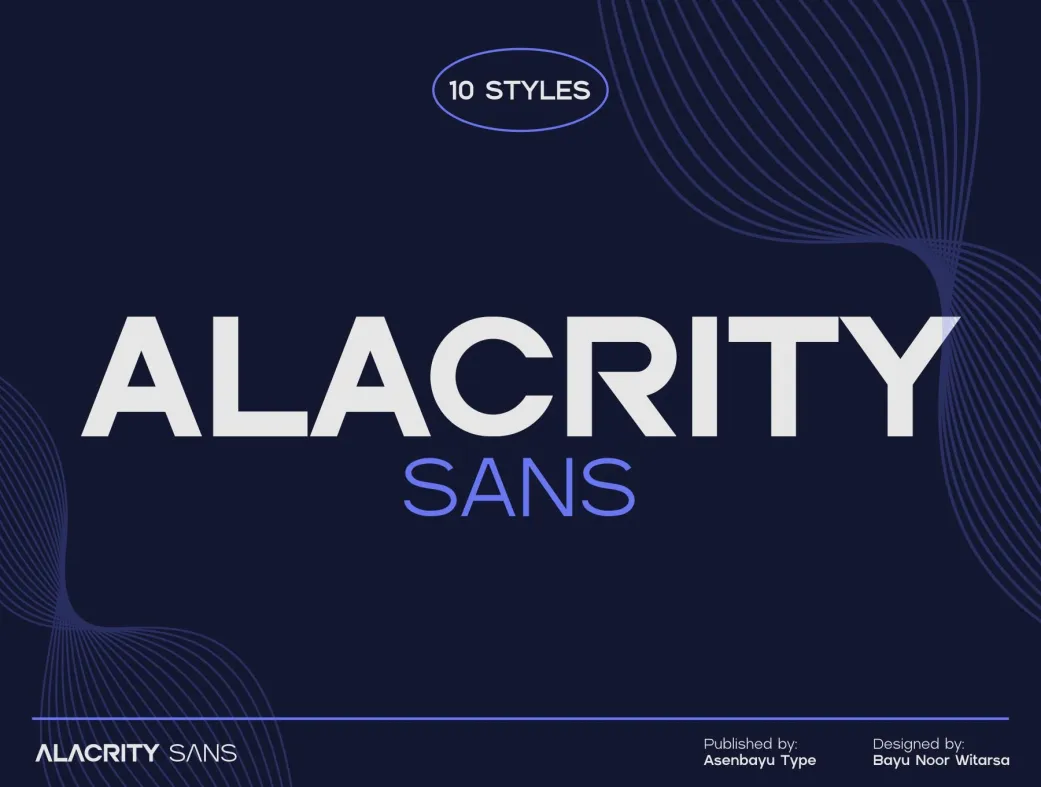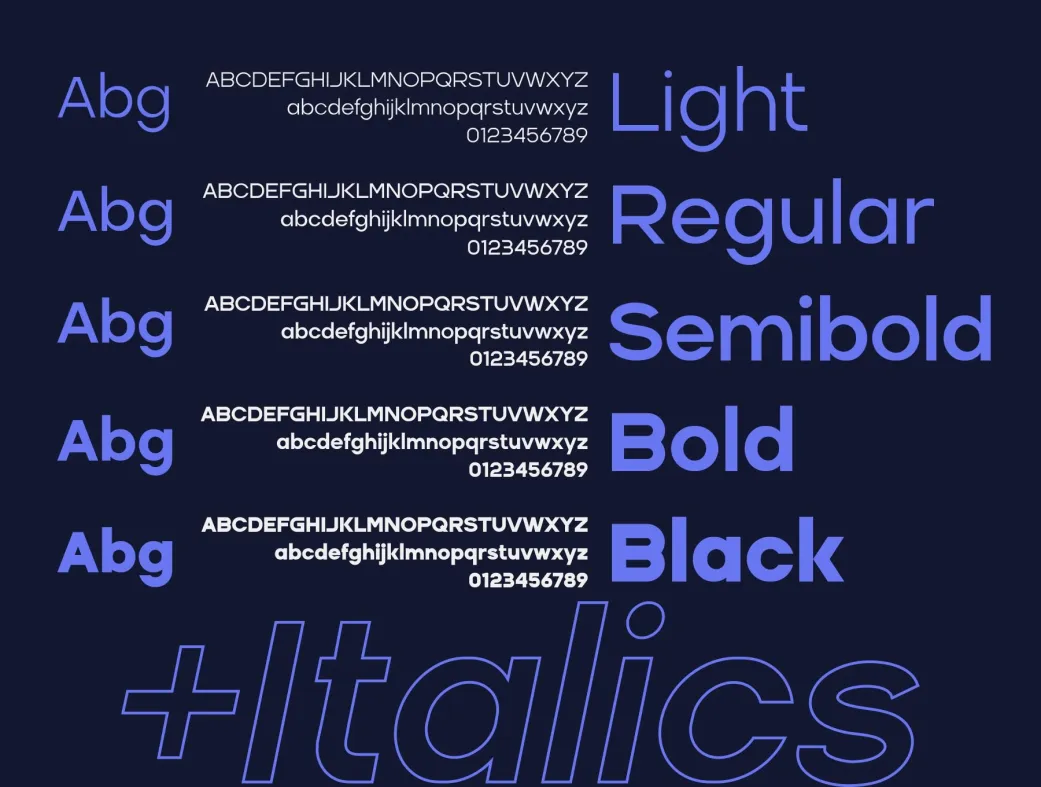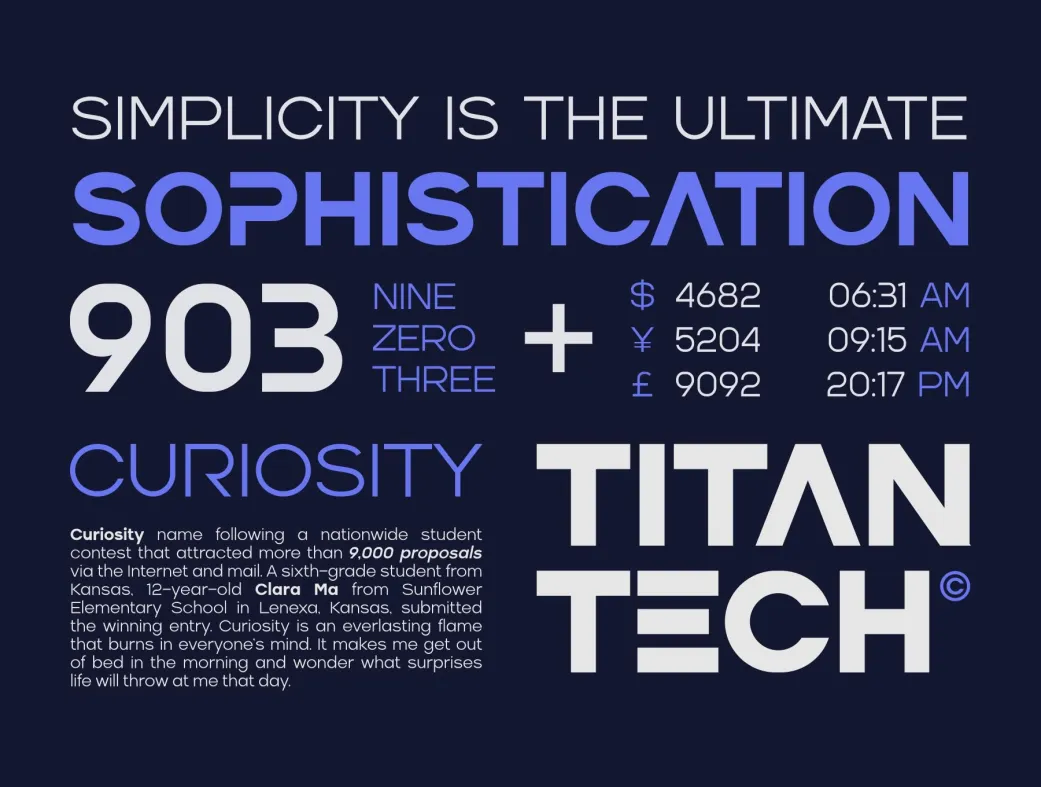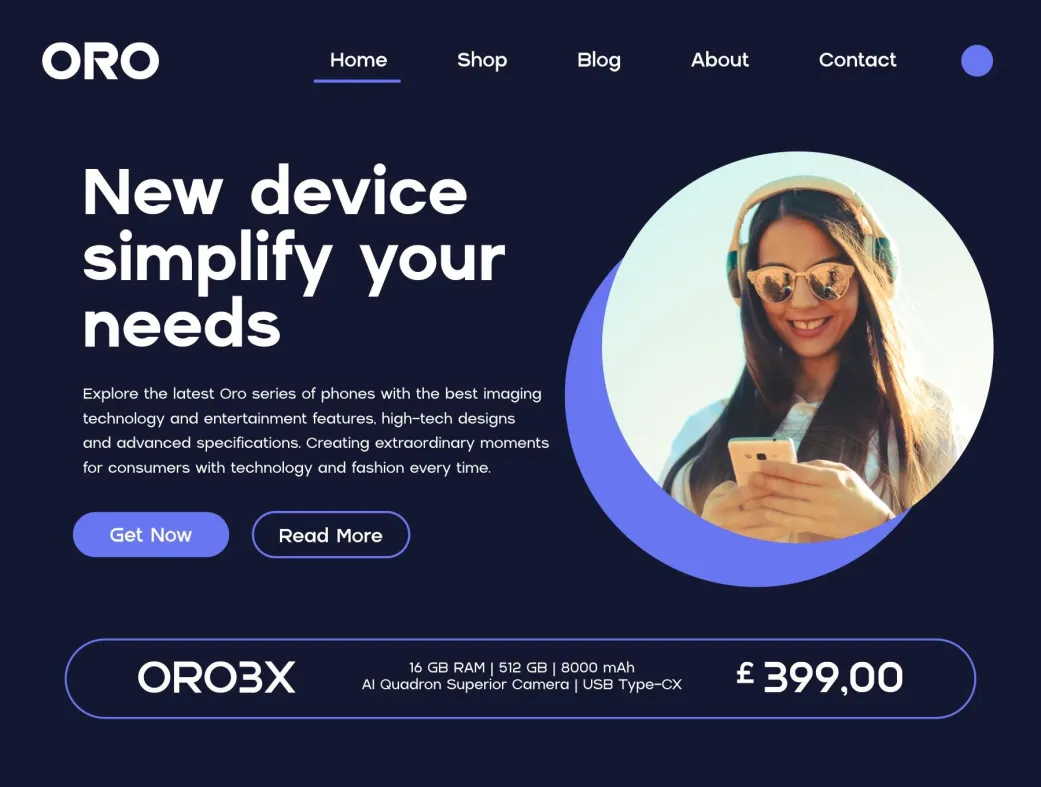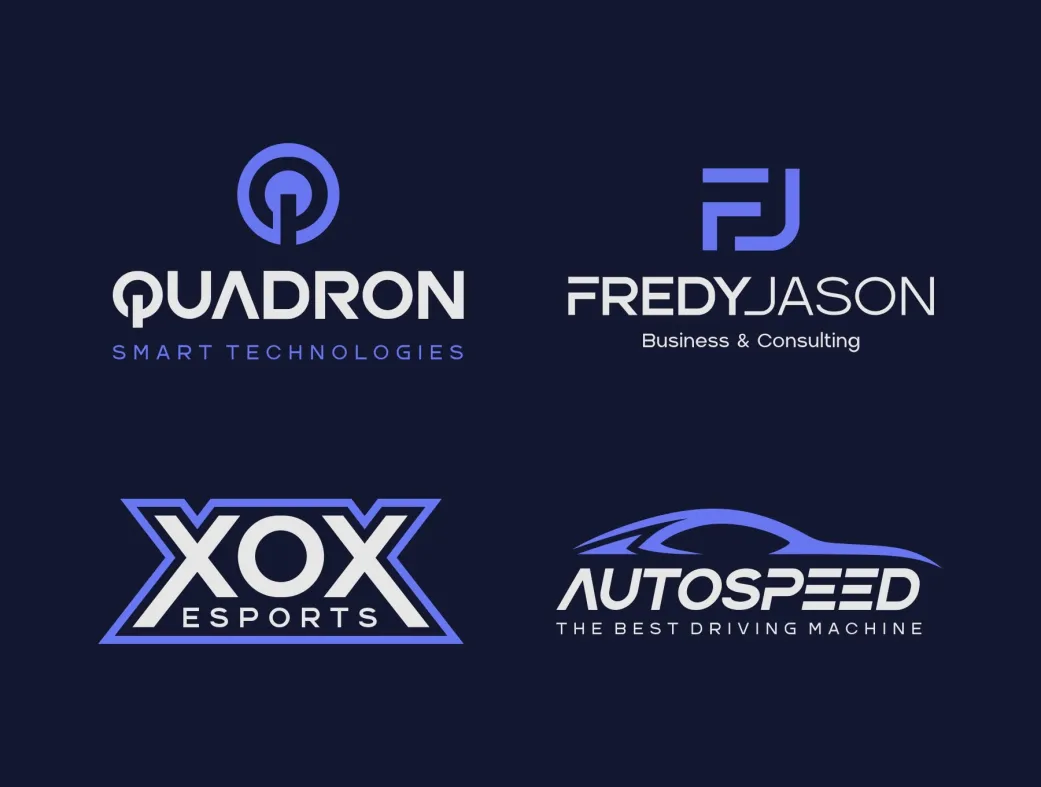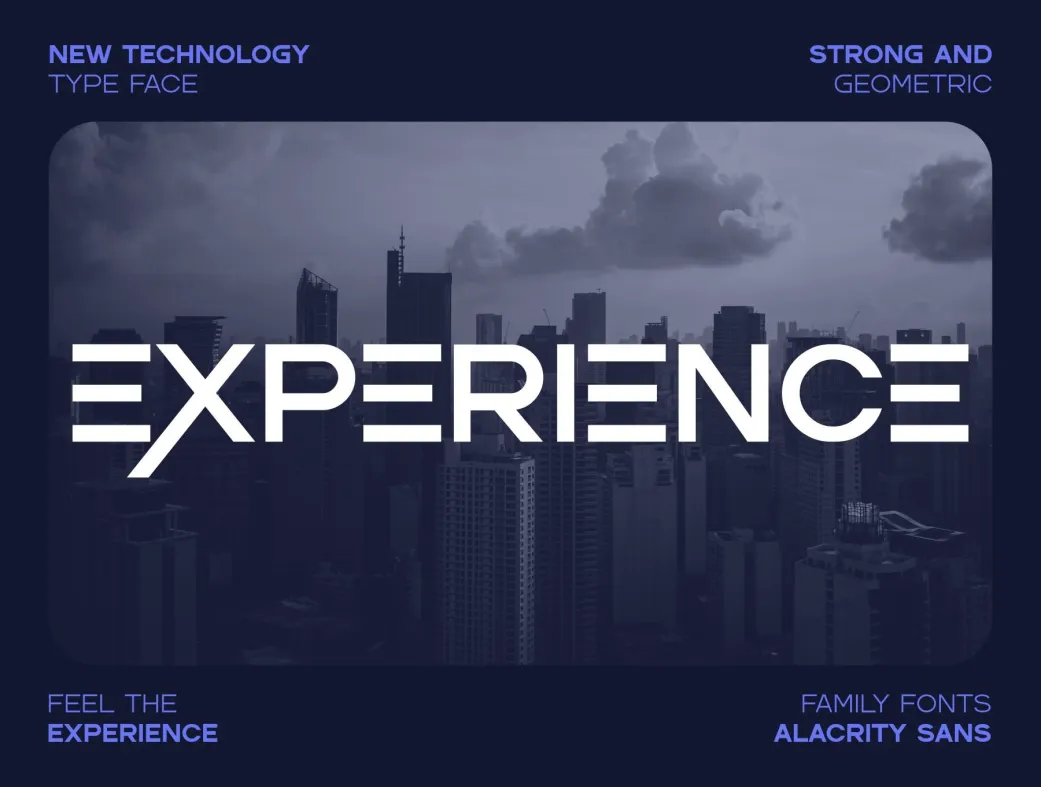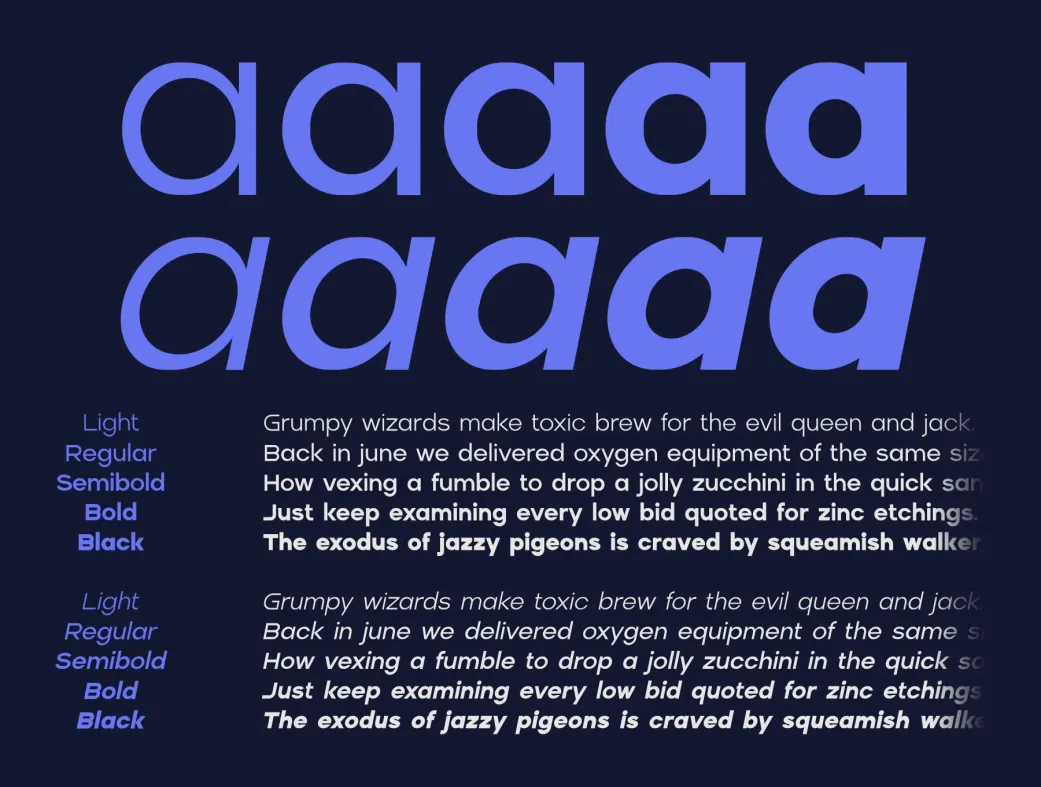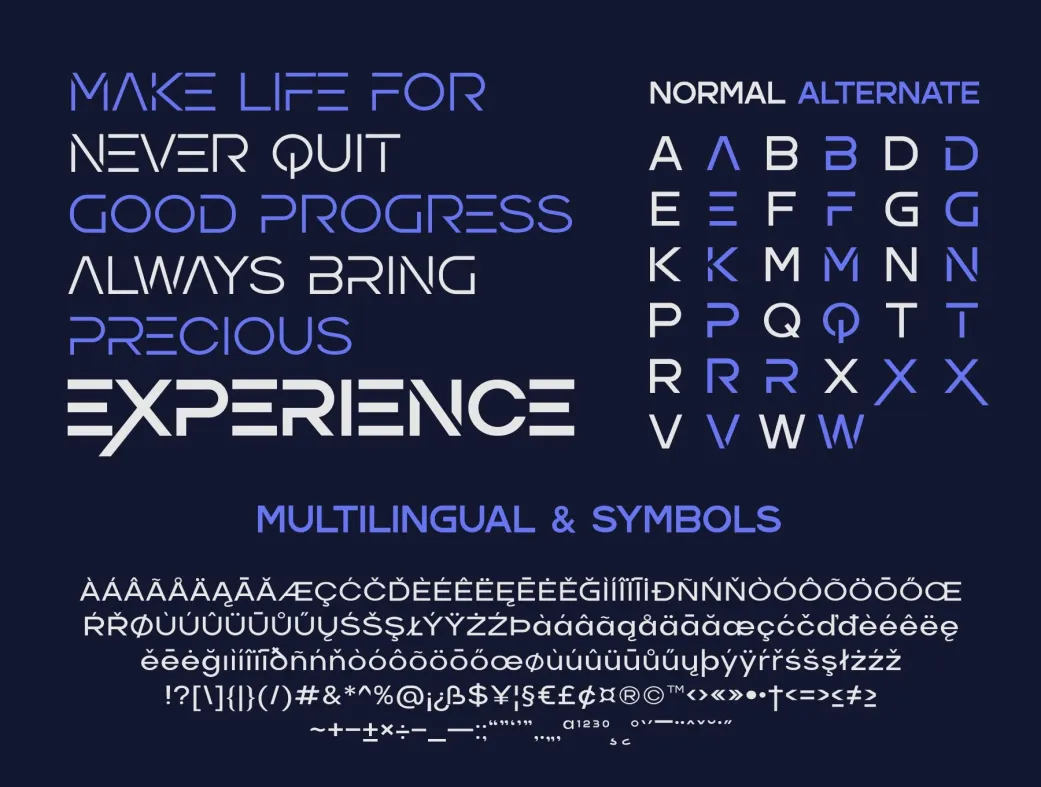
فونت فمیلی آلکریتی سانس
فونت هندسی مدرن و چندمنظوره برای طراحی‌های حرفه‌ای و خلاقانه.
Alacrity Sans Fonts Family
معرفی فونت فمیلی آلکریتی سانس
فونت آلکریتی سانس یک خانواده فونت sans serif چندمنظوره با اشکال هندسی پیچیده و مدرن است که برای طراحی‌های تمیز، حرفه‌ای و امروزی ایده‌آل می‌باشد. این فونت‌ها با الهام از فناوری‌های نوین تایپوگرافی ساخته شده‌اند و تجربه‌ای تازه از خوانایی و زیبایی بصری ارائه می‌دهند. اگر به دنبال فونت‌هایی هستید که در پروژه‌های متنوع مانند لوگو، هویت برند، کارت ویزیت، وب‌سایت‌ها، لوازم اداری، نمایشگرها، محصولات ورزشی و فناوری به کار روند، آلکریتی سانس انتخابی عالی است.
ویژگی‌ها و مزایای فونت آلکریتی سانس
این خانواده فونت با ۱۰ سبک متنوع (از Light تا Black، شامل ایتالیک) عرضه می‌شود و از ویژگی‌های پیشرفته OpenType مانند کرنینگ دقیق و جایگزین‌های استایلی پشتیبانی می‌کند. آلکریتی سانس نه تنها خوانایی بالایی در متن‌های طولانی دارد، بلکه در عناوین و المان‌های گرافیکی نیز برجسته عمل می‌کند. با پشتیبانی از چندزبانه، اعداد، علائم نگارشی و گلیف‌های استاندارد، این فونت‌ها برای طراحان وب، گرافیک و برندینگ ایرانی که به دنبال بهینه‌سازی سئو و جذابیت بصری هستند، ضروری‌اند.
کاربردهای فونت آلکریتی سانس در طراحی مدرن
از آلکریتی سانس برای ایجاد هویت بصری قوی در اپلیکیشن‌ها، وب‌سایت‌های شرکتی یا کمپین‌های تبلیغاتی استفاده کنید. این فونت با اشکال هندسی‌اش، حس نوآوری و دقت را منتقل می‌کند و در جستجوهای پرطرفدار مانند "فونت sans serif فارسی" یا "دانلود فونت هندسی مدرن" رتبه بالایی کسب می‌کند.